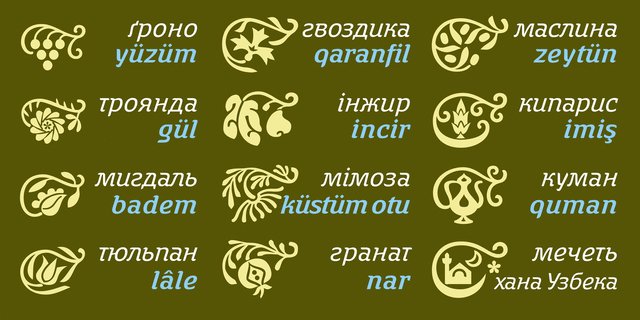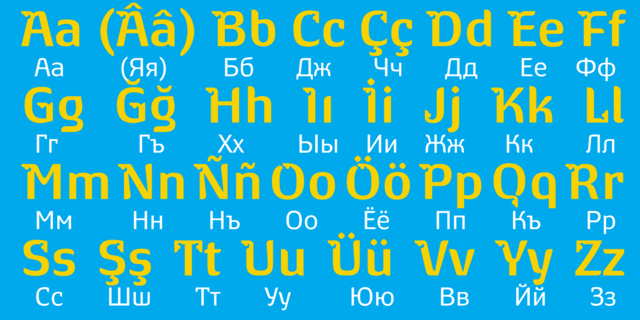
Основная цель гарнитуры Mustafa – восстановление шрифтовой идентификации для тюркских народов, перешедших из арабицы на латиницу или кириллицу. Впрочем, в тексте шрифт имеет достаточно нейтральный вид, пригодный для любых языков. Поддерживает европейскую, турецкую, крымскую, азербайджанскую латиницу; славянскую и тюркскую кириллицу. Содержит декоративные инициалы и флероны по мотивам народного орнамента крымских татар. Одинаково хорошо воспроизводится на экране и бумаге. Имеет дружественный читабельный вид, уместен среди прочего для детской литературы. Шрифт разработал Виктор Харик в 2019 году.
Функции начертания Mustafa BoldПрименение в макете:
Ассоциации c начертанием Mustafa BoldКачества и характер:
мягкий, приятный, уютный, комфортный, понятный, дружелюбный, добрый, вежливый, красивый, аккуратный, неторопливый, сочный, летний, семейный, домашний, органический, вкусный, здоровый, натуральный, природный, зеленый, свежий, доверительный, оригинальный, самобытный, интересный, пластичный, гибкий, гладкий, качественный, теплый, крымский, татарский, восточный, южный, азиатский, тропический